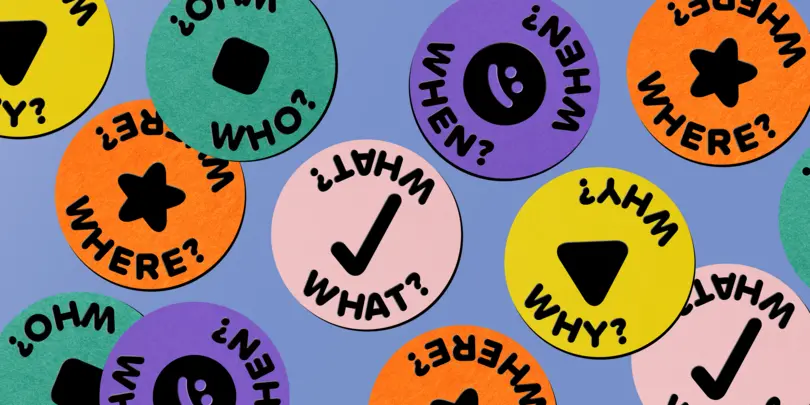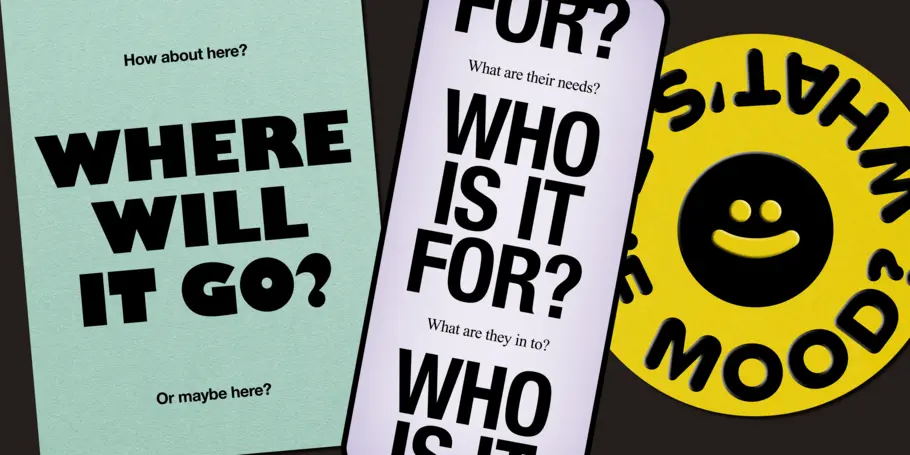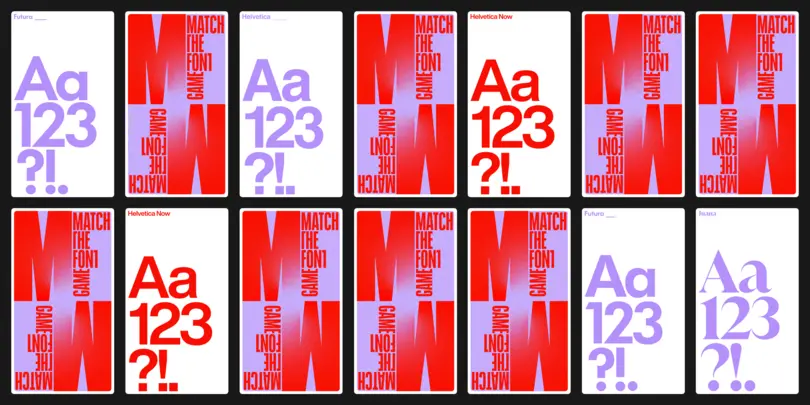
Choisir la bonne police pour votre projet.
“ Une fois que vous commencez à réfléchir de manière posée et à consacrer du temps à la sélection des polices, vos choix s'amélioreront. ”
«Comment choisir les bonnes polices de caractères ?»
Voici toutes les questions que j’ai reçues durant toute ma carrière de 20 ans en tant que designer ayant un amour particulier pour la typographie. Parfois, il a été difficile de les exprimer à travers des mots, alors je me suis assis pour écrire mon processus personnel et professionnel lorsqu’il s’agit de choisir les bonnes polices pour un projet.
Ce n’est pas de la science infuse, mais cela demande de la réflexion.
Si vous lisez ceci, je vais partir du postulat que vous comprenez pourquoi il est important de choisir précieusement les bonnes polices pour un projet. Sinon, pourquoi chercheriez-vous des conseils sur comment choisir les bonnes polices sur internet ? ;-) Avec cette supposition en tête, laissez-moi partager avec vous comment je choisis personnellement les polices de caractères.
En guise d’avertissement : il n’y a pas de grands secrets, pas de révélations majeures acquises au cours de mes 20 ans d’expérience en design et en typographie, mais cela pourrait être utile pour comprendre comment quelqu’un d’autre aborde ce processus de sélection des différentes options. Une fois que vous commencez à concentrer et à consacrer du temps à la sélection des polices, vos choix s’amélioreront.
Quelles sont vos exigences techniques ?
Comme pour tous les projets de design, je commence toujours par définir mes limites, mes contraintes, et à me poser des questions. Y a-t-il des exigences spécifiques pour l’utilisation de vos polices ? Avez-vous besoin de typographie principalement pour des panneaux d’affichage géants ou pour de petites exigences légales au bas d’une publicité télévisée ? Concevez-vous quelque chose destiné à être lu à l’écran ou sur papier ? Votre produit est-il une interface utilisateur d’application mobile ou un article long ou encore un livre imprimé ? Aurez-vous besoin d’un support linguistique spécifique maintenant ou à l’avenir ?
D’après mon expérience, j’ai constaté que les projets de branding et de design ont une myriade d’applications ; aussi bien pour l’affichage en grand format que pour le texte en petit format. Dans ce cas, je suggère de choisir une police de caractères qui a plusieurs tailles optiques spécifiquement conçues pour différentes tailles de caractères. Une police avec des tailles optiques à des designs légèrement différents pour l’affichage en grand format, les titres moyens, et le petit texte. Toutes les tailles optiques travaillent à l’unisson pour rendre la typographie similaire et cohérente dans toutes les tailles d’application. Il y a différents noms pour les tailles optiques en fonction du designer de la police, mais généralement il y aura une taille «titrage», «texte» et “micro” pour les notes de bas de page que vous pouvez simplement considérer comme Grand, Moyen, et Petit et les appliquer en conséquence.
Personnellement, je suis un grand fan de l’utilisation des polices monospaces pour toute petite information ou pour l’affichage de n’importe quelle donnée. Les polices monospaces sont des polices où chaque caractère a exactement la même largeur et cela donne immédiatement le sentiment d’une information logique et rationnelle. Je les utilise tout le temps pour les légendes de photos, les détails juridiques, et chaque fois que j’ai besoin de montrer des données ou des faits de manière convaincante.
Enfin, considérez votre public et à quel point votre produit devra s’exporter à l’international. Si vos utilisateurs vont lire ou utiliser les polices dans plusieurs langues, assurez-vous que le support linguistique et les accents sont inclus dans les polices que vous choisissez. Vous ne voulez pas arriver à mi-chemin d’un projet avec une certaine police et vous rendre compte qu’elle n’a pas de tréma ou de circonflexe au-dessus des caractères et que vous devez revenir à la case départ pour rechercher une nouvelle police de caractères.
Qui est votre public ?
En lien avec le support linguistique, je me demande toujours qui va utiliser mes designs ou mon produit : L’audience est-elle jeune ou âgée ? Est-elle experte en technologie ou en cours d’apprentissage ? Utilise-t-elle un matériel là jour ou légèrement en retard technologiquement ? Les utilisateurs viennent-ils d’un lieu géographique spécifique ou seront-ils dans le monde entier ?
Comme vous le savez probablement, concevoir pour une revue académique aura une esthétique visuelle différente des images que vous pourriez créer sur TikToks ou Instagram . Si vous cherchez une police de caractères qui semble à la mode, assurez-vous de consulter le Rapport sur les tendances 2023 de Monotype pour voir les tendances et les styles visuels à travers le monde. Si vous avez besoin d’une approche plus «classique», envisagez une serif comme Cotford de Tom Foley et le Monotype Studio, Macklin de Malou Verlomme et le Monotype Studio, ou Paperback de John Downer et House Industries.
Si vous avez une charte graphique existante, vous allez évidemment devoir rester dans ces garde-fous, mais ne désespérez pas - il peut encore y avoir de la place pour l’expérimentation ! Au cours de ma carrière, j’ai été surpris de voir à quel point je pouvais pousser les directives de la marque en faisant des choix éclairés ou en utilisant les polices existantes de manière inattendue.
Un autre conseil : Pour m’assurer que je ne fais pas simplement une copie de ce qui a déjà été fait, je crée souvent rapidement un mood board de ce que d’autres ont fait dans un domaine similaire. Vous concevez une nouvelle marque pour une entreprise technologique ? Je vous supplie de ne pas simplement utiliser une autre sans-serif géométrique ! Si tous vos concurrents utilisent la même chose, essayez l’opposé pour distinguer votre produit. Si tout le monde a déjà récemment utilisé la police «farfelue, des années 70, groovy, à la Patagonia» ? Je dirais plutôt de choisir quelque chose d’expressif qui distingue votre design.
Choisissez le contraste.
Choisir des polices de caractères qui se contrastent est mon approche de prédilection pour trouver les bonnes polices. Choisir Helvetica et Futura (deux sans-serif) ne me donne pas assez de contraste visuel, même si elles sont techniquement différentes (Helvetica est une néo-grotesque et Futura est une sans-serif géométrique).
Ma meilleure idée est de trouver des polices de caractères conçues par la même personne, et de choisir une serif et une sans-serif parmi elles. Les designers ont leur propre approche de la conception typographique et cela peut souvent se voir entre des designs de styles évidemment très différents. Même lorsque deux polices sont de genres très différents, j’ai constaté qu’il semble y avoir une harmonie entre les designs parce que la personne qui les a conçus est la même. Ce n’est bien sûr pas vrai pour tous les designers ou situations, mais cela m’aide souvent à réduire les polices qui se ressemblent.
Choisir une paire de serif et de sans-serif est presque infini dans ses possibilitées, mais mon conseil de prédilection est de choisir un design de serif avec beaucoup de poids et de contraste (des serifs minces ou épais avec des futs contrastées). Une fois que vous avez choisi la serif, trouvez une police sans-serif que vous aimez et associez-la à un poids plus léger que le poids normal. Ce poids plus fin d’une sans-serif peut être utilisé pour un effet dramatique à des tailles d’affichage plus grandes, ce qui est une approche un peu inhabituelle, mais qui donnera une touche de fraîcheur au design.
Construisez votre famille.
Vous trouverez de nombreux guides pour créer une paire de polices de caractères, mais j’aime créer un trio de polices de caractères pour une flexibilité maximale pour les mélanger et les assortir à volonté. Choisir un trio de titrage, de texte et de micro-taille vous donne beaucoup d’opportunités pour établir une solide fondation typographique ainsi que pour jouer avec.
Comme exemple de choix de polices de caractères du même designer (ou dans ce cas, de deux designers), je choisirais le trio talentueux de designers de chez Process Type Foundry : Colfax pour le travail de titrage, Elena pour le corps du texte et la lecture plus longue, et la police monospaced Recipient pour les légendes, le texte juridique et la visualisation des données. Si vous ne pensez pas qu’une monospaced fonctionne dans votre projet, je suggère vivement quelque chose comme Operator qui a le style visuel d’une mono mais qui est toujours proportionnelle et attire un peu moins l’attention sur elle-même.
E-101_Match_The_Font_2880x1440_148
Cela demande de la pratique.
Une chose que je ne veux pas minimiser, c’est que choisir les bonnes polices de caractères pour les projets prend du temps, de la pratique et de l’expérience. Si vous ne choisissez pas un bon trio de polices dès le départ, ne vous découragez pas ! Je lutte encore avec l’association et la sélection des polices, et je fais cela depuis presque 20 ans. Comme pour la plupart des choses valables dans la vie ; plus vous faites une chose, meilleure sera votre perception de la typographie, votre jugement des associations, et vos choix seront meilleurs.